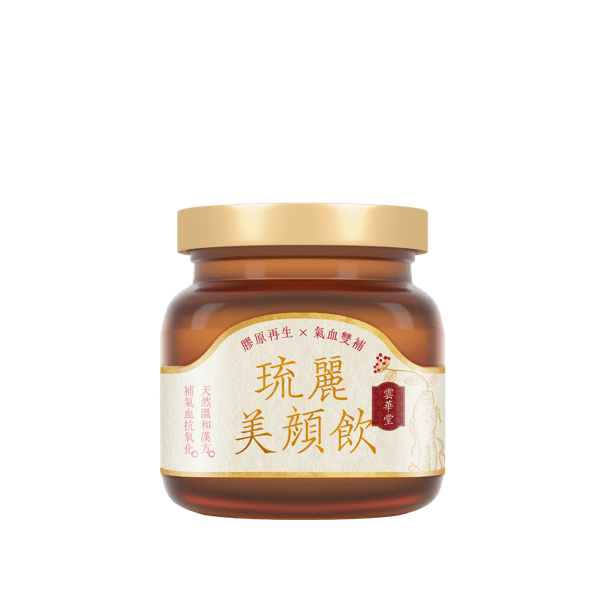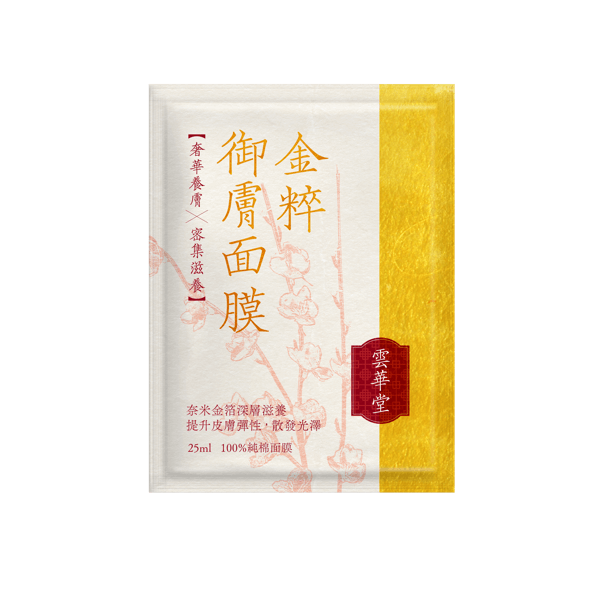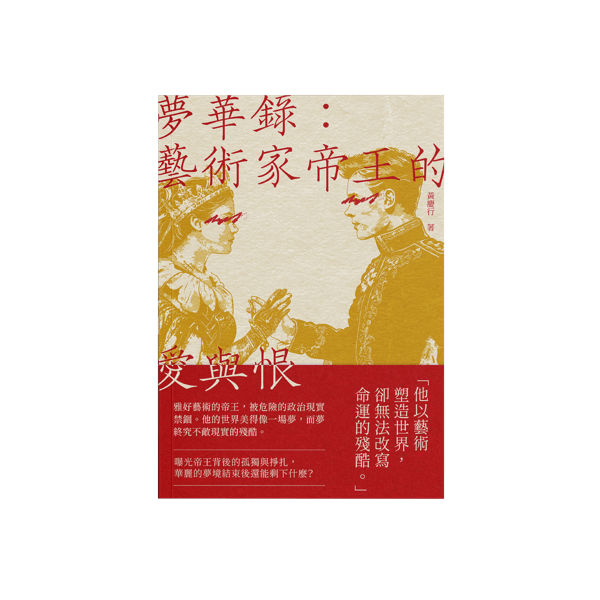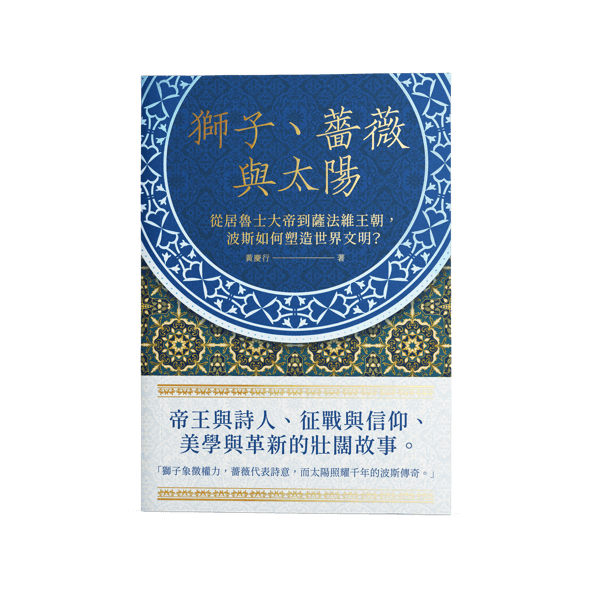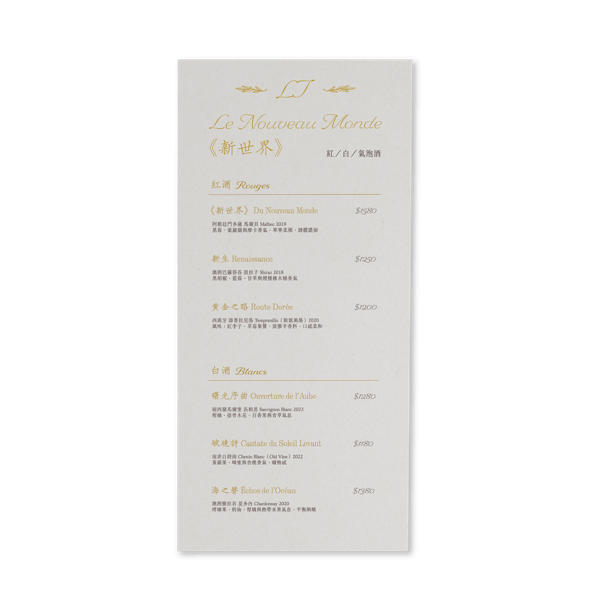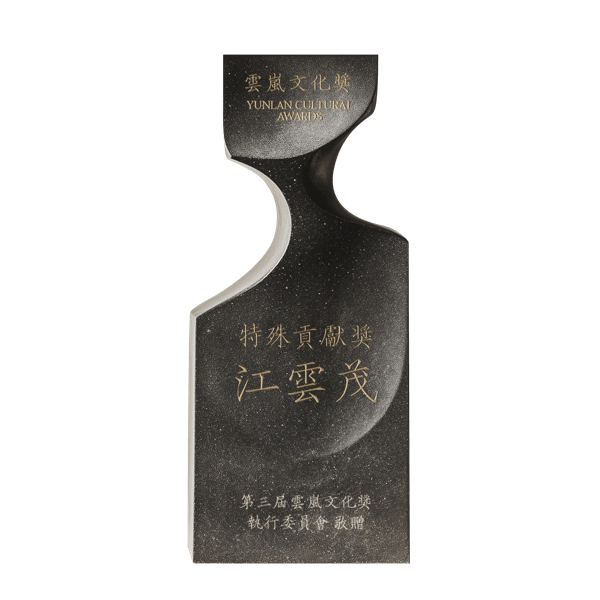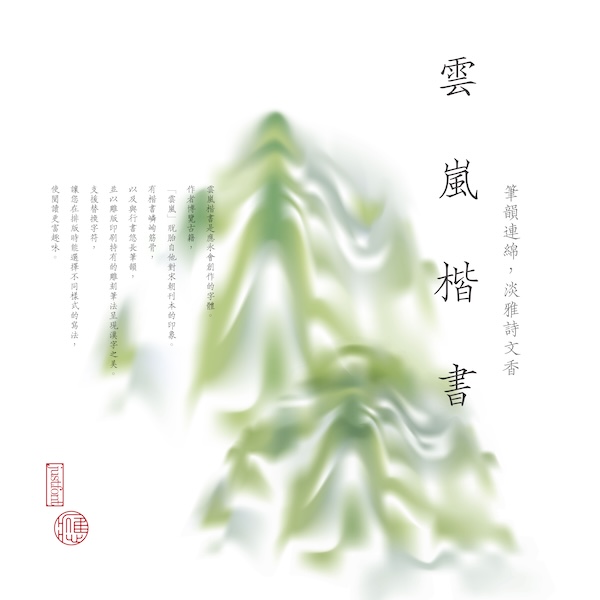
雲嵐楷書
雲嵐楷書是應永會創作的字體。作者博覽古籍,「雲嵐」脫胎自他對宋朝刊本的印象。有楷書嶙峋筋骨,以及與行書悠長筆韻,並以雕版印刷特有的雕刻筆法呈現漢字之美。支援替換字符,讓您在排版時能選擇不同樣式的寫法,使閱讀更富趣味。
應永會
中國浙江寧波出身,雅好古籍,平時也創作插畫。從 2007年起開始創作漢字字體,「汲古書體」、「浙江民間書刻體」是他的代表作。屏棄現代規格模組化的造字流程,應永會一筆一畫描繪出漢字的靈活多變,有如數位時代的雕版匠師。